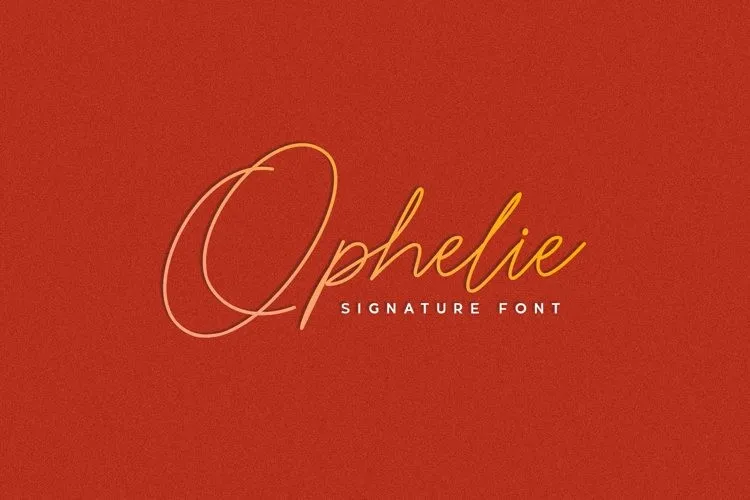
Ophelie Font
A ‘Ophelie Font’ é uma elegante fonte signature monoline criada pelo designer Adriansyah que traz uma impressionante aparência. Essa fonte é perfeita para um design criativo, seja ele para redes sociais e marcas, embalagens de produtos, convites de casamento, sinalização, etiquetas, assinaturas, capas de livros ou revistas, outdoors, citações, entre outros usos. Um benefício adicional é a ‘Bold Sans’, outra fonte que combina perfeitamente com ‘Ophelie Font’. Essa fonte é uma ótima escolha para designers em busca de um estilo elegante e minimalista que se destaca na cena do design. A ‘Ophelie Font’ oferece um conjunto de cores diversificado, permitindo um uso sofisticado e criativo. É a escolha perfeita para criar um design impecável e moderno que chamará a atenção dos seus clientes ou leitores.